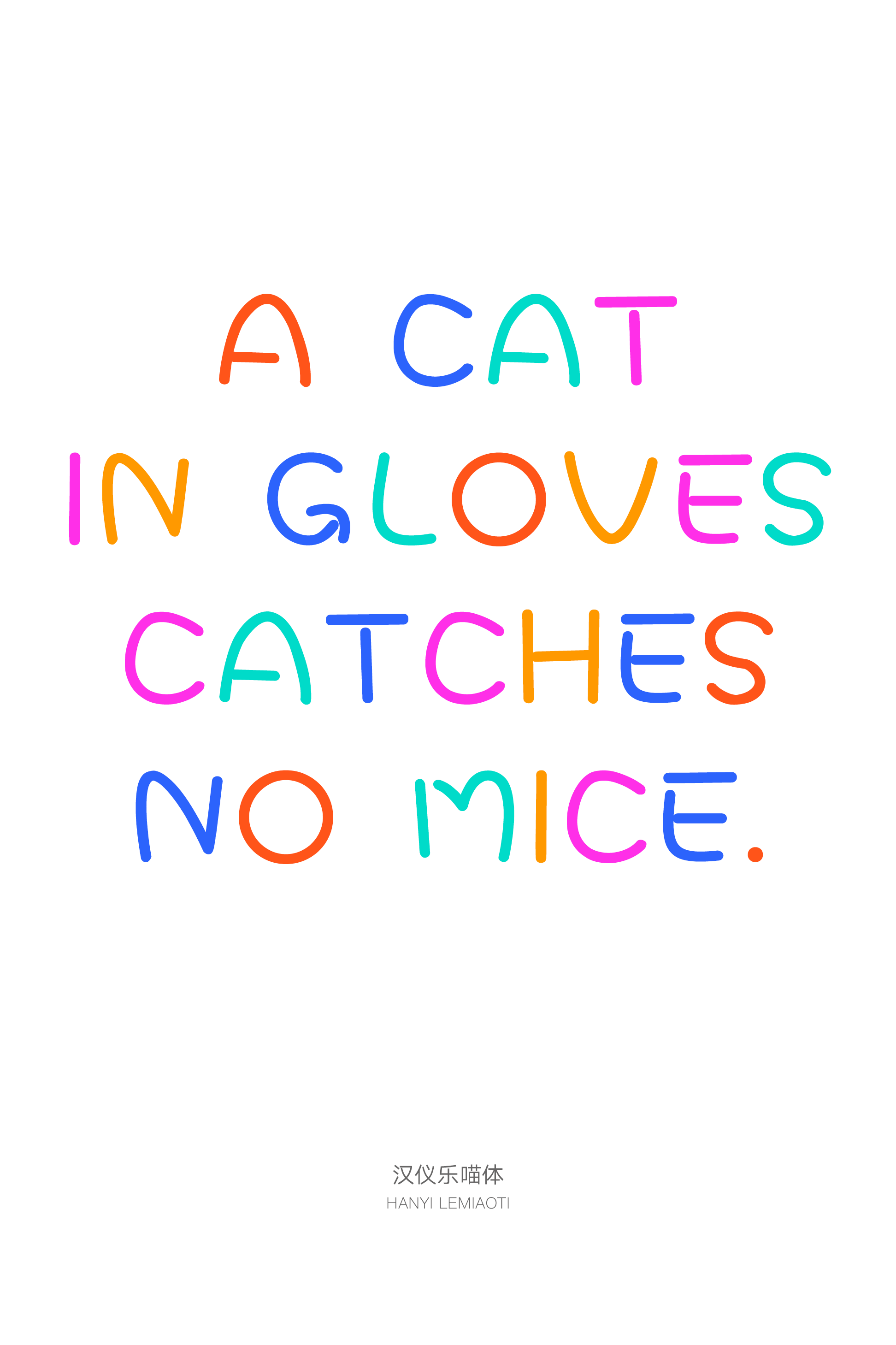
汉仪乐喵体
人们向往着轻松愉快又充满惊喜的生活,对于字体也是如此。汉仪乐喵体用单纯的线条语言表达跃动的韵律,传递活泼、可爱、亲切之感,回归童真,在繁杂的社会中还原真实的生活感受。这款轻松有趣的漫画风格手写字体在绘本动画、玩具及食品包装、影视综艺等使用场景中令人眼前一亮,开启快乐的心情。
字形活泼跳跃,无拘无束。
圆头的笔画线条单纯而简约。
书写自由,活泼可爱。
西文部分以相同的单纯线条构成,可爱翻倍。